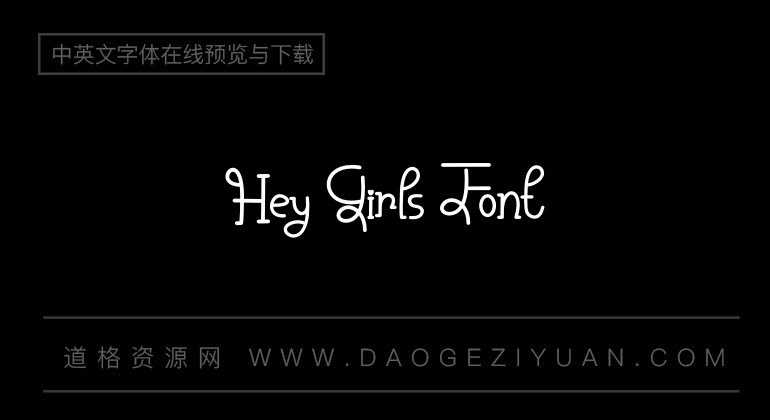
Hey Girls Font
Hey Girls Font 是一种流行的手写风格字体,主要用于女性品牌、时尚博客、婚礼邀请函、海报设计等场合。它的字母形状柔和、优雅,带有一定的手写风格特色,让文本看起来更加亲切、柔美。Hey Girls Font 包含大写字母、小写字母、标点符号和数字,同时还提供多种替代字形和连字,以满足不同设计需求。
Hey Girls Font是一款非常不错的手写艺术字体,具有很好的视觉感,适合于文化类的宣传设计、商业类品牌的广告和产品包装设计以及个性化文字排版等较多场景。